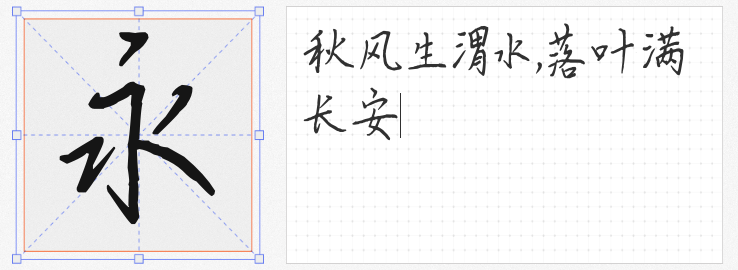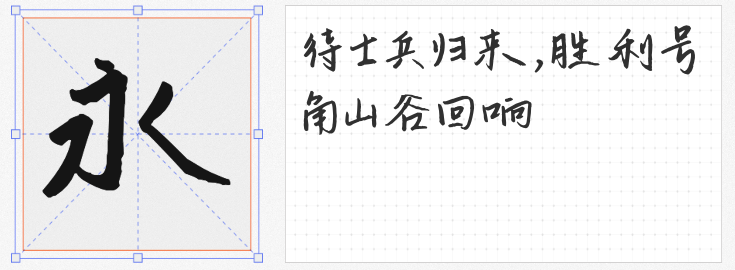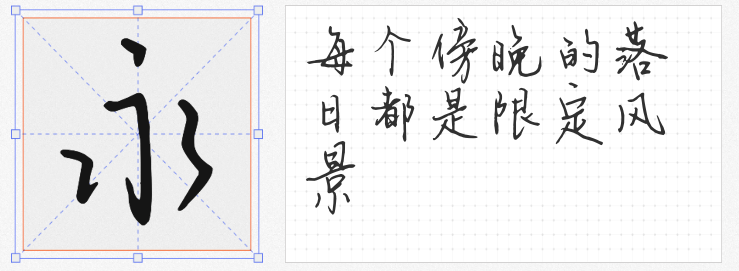
四款清新手写体推荐:免费商用字库中的海报设计宝藏
在海报设计的创意海洋中,字体是传递情感与风格的关键航标。对于追求清新文艺感的设计师而言,一款契合主题的手写字体往往能成为点睛之笔。今天推荐四款来自云峰字库与平方字库的免费商用手写字体,它们以独特的清新气质与实用性,成为海报设计的理想选择。
1. 她屿山海
由云峰字库出品的「她屿山海」,以纤细灵动的笔画勾勒出日记手写的私密感。每个字都像带着淡淡的墨香,字间距自然舒展,仿佛能让人听见笔尖划过纸面的沙沙声。这款字体尤其适合文艺类海报,无论是电影宣传、手账周边还是诗歌展陈,都能以不加修饰的真诚感打动观众。
2. 云峰林桥体
同为云峰字库力作的「云峰林桥体」,以近乎执拗的工整性颠覆传统手写字的随性印象。横竖撇捺间透着严谨的几何美感,却因适度的弧度保留了手写温度。这款字体在需要传递可靠感的海报中表现卓越,如教育机构宣传、产品说明书或文化讲座海报,工整而不失人文气息。
3. 平方长安体
平方字库的「平方长安体」将硬笔书写的张力演绎得淋漓尽致。纤细笔画中蕴含着书法特有的筋骨感,中宫收紧的结构让文字排列如诗行般错落有致。其婉约连笔既保留了书写流畅性,又避免了过度装饰的浮夸。这款字体在茶饮品牌、国风展览等场景中,能完美平衡现代审美与传统意蕴。
4. 平方将军体
「平方将军体」以适中的笔触粗细与鲜明的视觉层次脱颖而出。它既保留了书法字体的艺术张力,又通过标准化处理确保了远距离的可读性。无论是网页标题、包装设计还是书法字帖创作,这款字体都能以独特的存在感吸引目光,同时维持整体画面的和谐感。